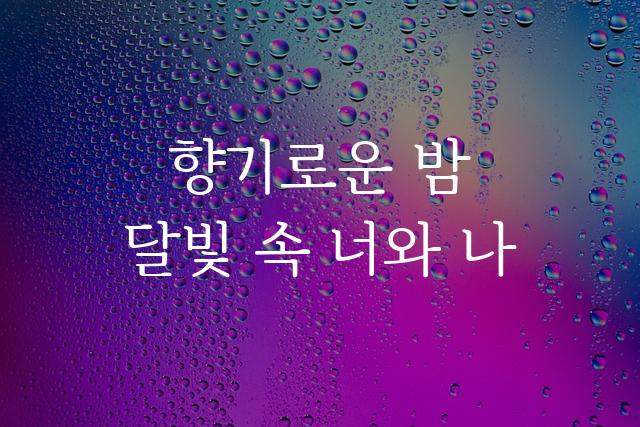
김포평화제목 폰트는 김포시에서 제작한 기본 고딕과 장식 고딕이 어우러진 독특한 디자인을 자랑합니다. 이 폰트는 현대적 감각과 전통적 요소가 조화를 이루며, 다양한 디자인에 유연하게 적용될 수 있습니다.
김포평화제목은(는)
기본 고딕, 장식 스타일, 감성적인, 부드러움, 별모양/패턴 계열의 생김새를 가지고 있으며
로고 디자인, 제품 포장, 출판물 제목 등에서 자주 활용되며, 효과적인 메시지 전달에 적합합니다.
이 폰트는 광고/마케팅, 소매/유통, 금융/비즈니스 분야에 잘 어울리며,
신뢰감, 명확한, 전문적인 느낌을 담고 있는 것이 특징입니다.